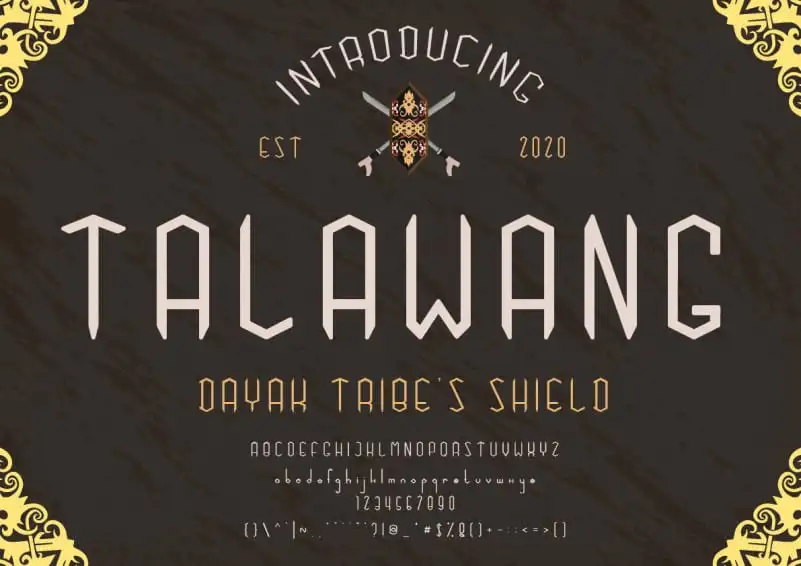
Talawang Display Font – Download Grátis
A Talawang Display Font é uma elegante e versátil fonte para exibição que traz elementos serifados. Inspirada no Shield de Talawang, uma armadura protetora característica das sociedades Dayak, essa fonte pode ser usada para criar tanto estilos simples quanto títulos e textos incrivelmente atraentes. Seu design permite escolher entre muitas letras alternativas, tornando-a perfeita para qualquer projeto que você possa imaginar. A Talawang Display é uma excelente adição à sua biblioteca de fontes, capaz de dar um toque retro e sofisticado aos seus materiais. Com seu design inspirado na cultura Dayak, a Talawang é mais do que apenas uma fonte moderna – ela oferece uma conexão com a história da humanidade através de suas linhas sutis e elegantes.